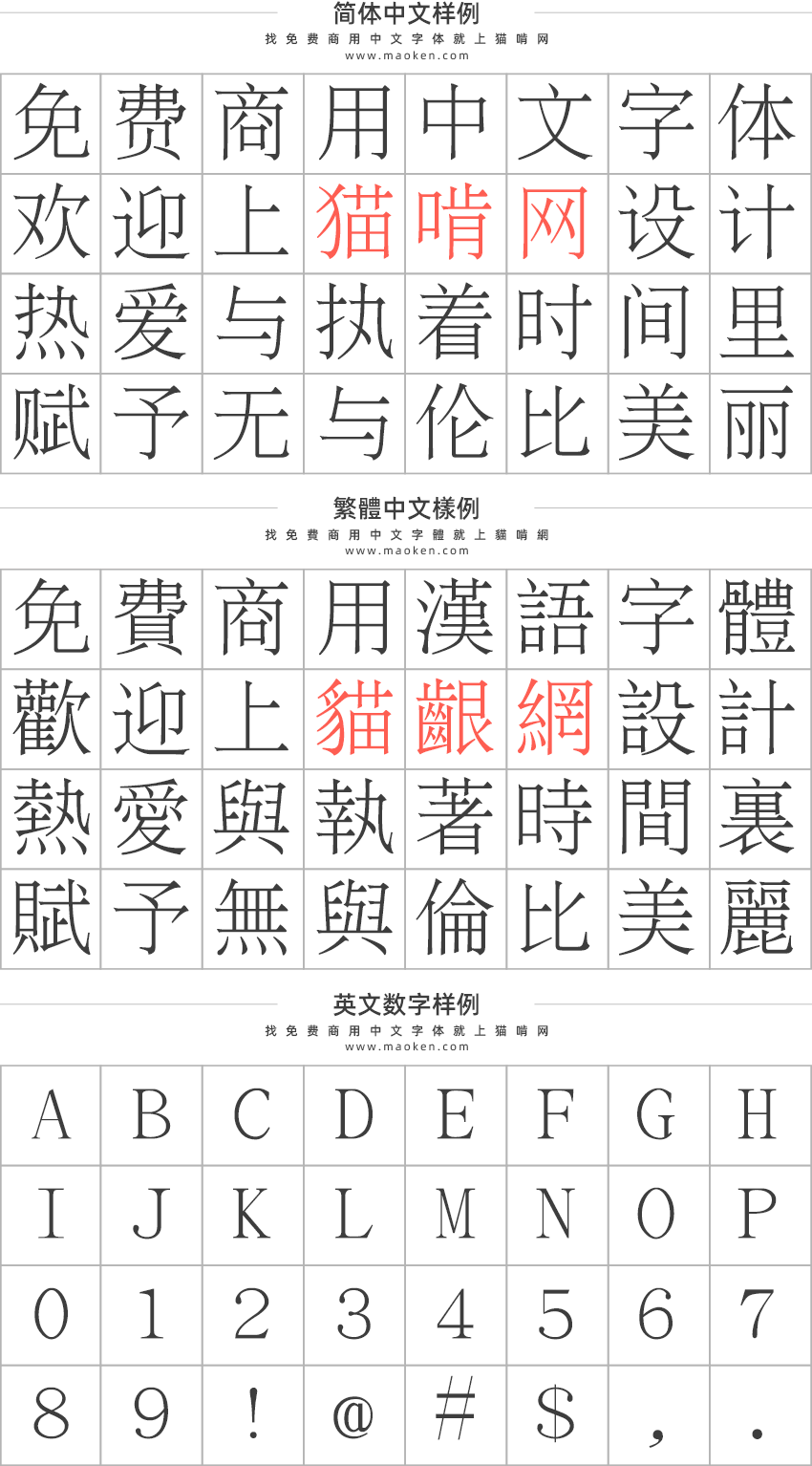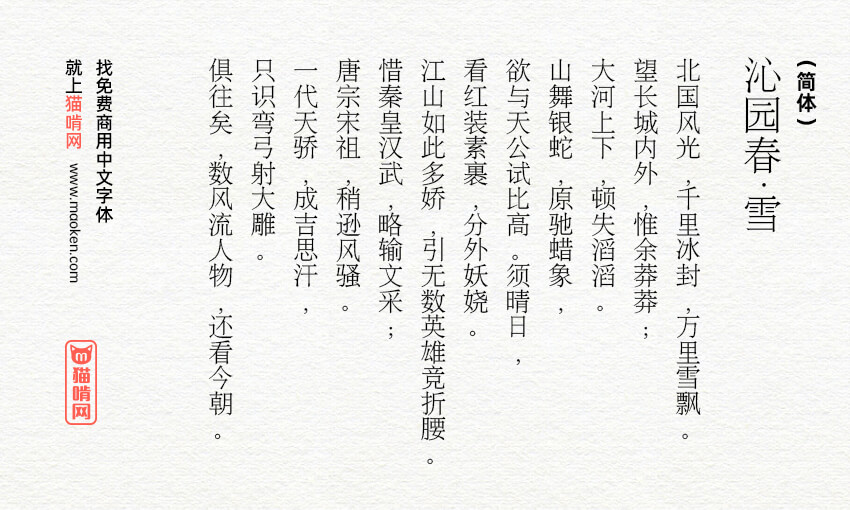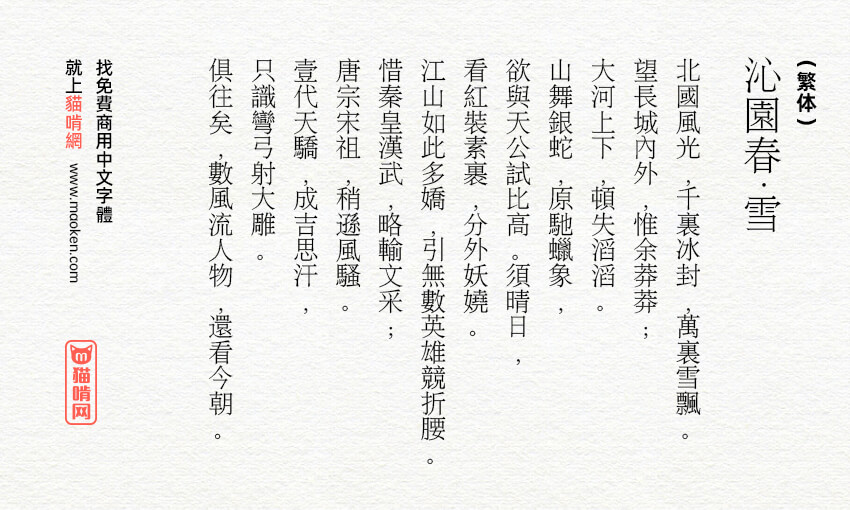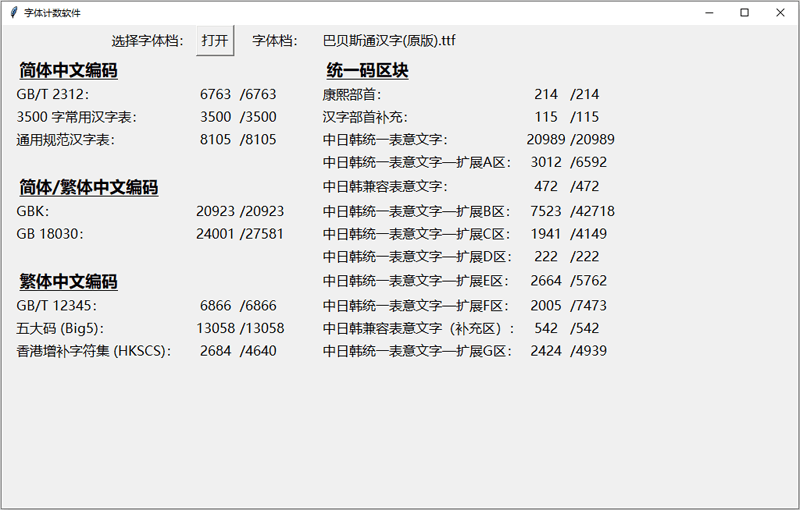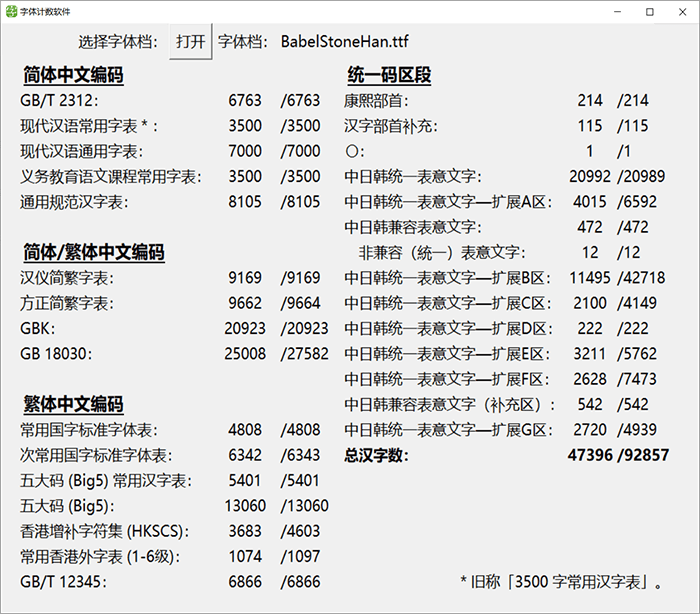
巴贝斯通汉:BabelStone Han 字型超过四万零五百个汉字免费商用
字体作者:ANDREW WEST (英国) 字体字重:1个
巴贝斯通汉是一种免费的 Unicode CJK字体,拥有超过 46,500 个汉字(hanzi、kanji、hanja)和 57,460 个 Unicode 字符。它是一种宋体/明体(宋体/明体)字体,字形仿照中华人民共和国使用的官方字符形式,主要用于书写现代标准汉语、古典汉语以及各种汉语语言和方言. 但是,它还包括大量用于日语、韩语、越南语 ( Chữ Nôm ) 和壮语 ( Sawndip)。对于中文,它既涵盖了繁体字,又涵盖了简体字(它全面覆盖了Unicode中包含的所有中文简体字,以及所有对应的繁体字)。该字体还包括许多在大多数中日韩字体中找不到的稀有或古老的字符,以及许多用于书写在骨、青铜、木、竹和丝绸上的早期中文文本的学术转录的字符。此外,私人使用区提供了超过 5,200 个未编码的汉字(也可以使用单独的BabelStone Han PUA字体)。当前版本的 BabelStone Han 支持Unicode 13.0 * 于 2020 年 3 月 10 日发布。
* 列出了 Unicode 版本 13.0 中 CJK 统一表意文字的所有IDS序列的纯文本文件作为IDS.TXT 提供。
BabelStone Han 由文鼎科技(文鼎科技)于 2001 年发布的“AR PL Mingti2L Big5”字体(13,068 CJK Unified Ideographs)和“AR PL SungtiL GB”字体(6,763 CJK Unified Ideographs)合并而成。原始Arphic Public License [见下文]。包含 14,907 个 CJK 统一表意文字的合并字体随后被转换为 Unicode 映射,并在此后得到扩展,以涵盖 CJK 和 CJK 扩展 A、B、C、D、E、F 中的各种繁体和简体字符。 G 块,以及许多通用的 Unicode 字符。原始 CJK 字形已在适当的地方进行了修改,以匹配 Unicode 代码表中给出的 G 源字形。
该字体正在不断开发中,因为计划在未来几年内将数以万计的其他 CJK 表意文字包含在 Unicode 中。我打算尽可能多地将这些新字符添加到 BabelStone Han 中,但我永远无法将所有已经和将添加到 Unicode 的 CJK 表意文字包括在内,所以我专注于 G 源添加(即在中国使用的字符)。但是,如果您想紧急添加任何字符到 BabelStone Han 中,请告诉我(通过twitter或电子邮件),我将尝试快速跟踪它们在字体中的包含。如果您发现任何字形错误,也请告诉我。
关于字体作者
魏安(ANDREW WEST,1960年-),英国语言学家。他原来专门研究明清小说,对《三国演义》的版本进行了全面、细致的研究,提出新的方法来分析各个版本的关系,从而推断《三国演义》的原来面貌。他现在专长于中国少数民族语言文字,尤其是辽、金、元三朝的文字。他近来提出八思巴字编码方案,经过中国、蒙古及外国学者的研讨合作于2006年收入UNICODE 5.0版。
这个字体和方正报宋以及台湾明体很像,字模撑得比较满,适合报纸排版。
• 美中不足是内置的标点符号不支持竖排。